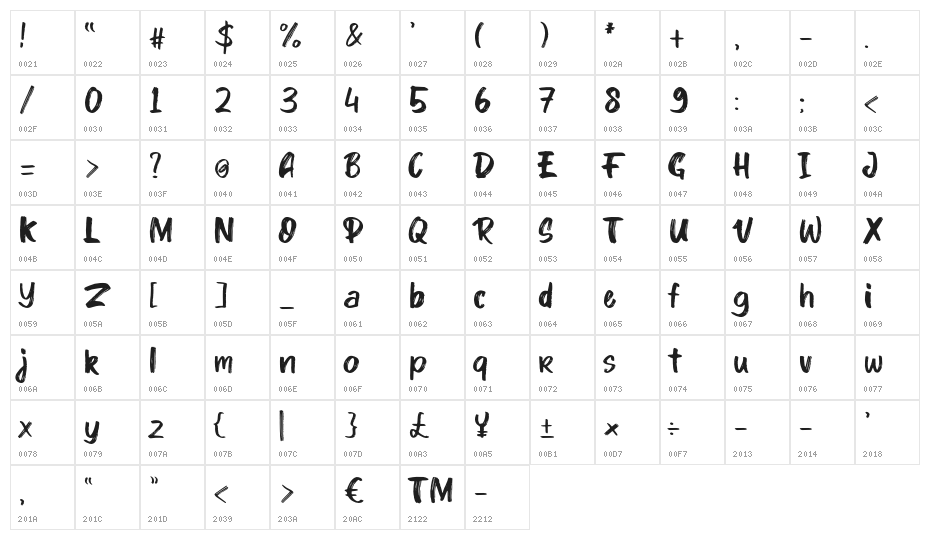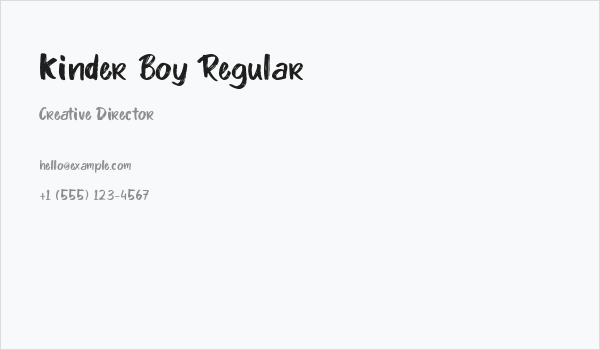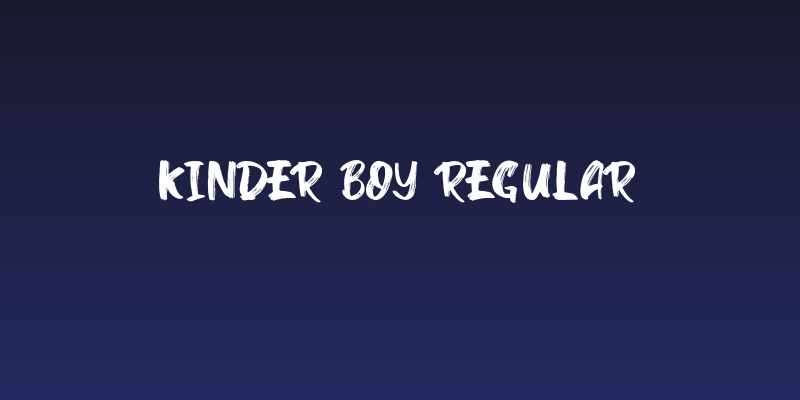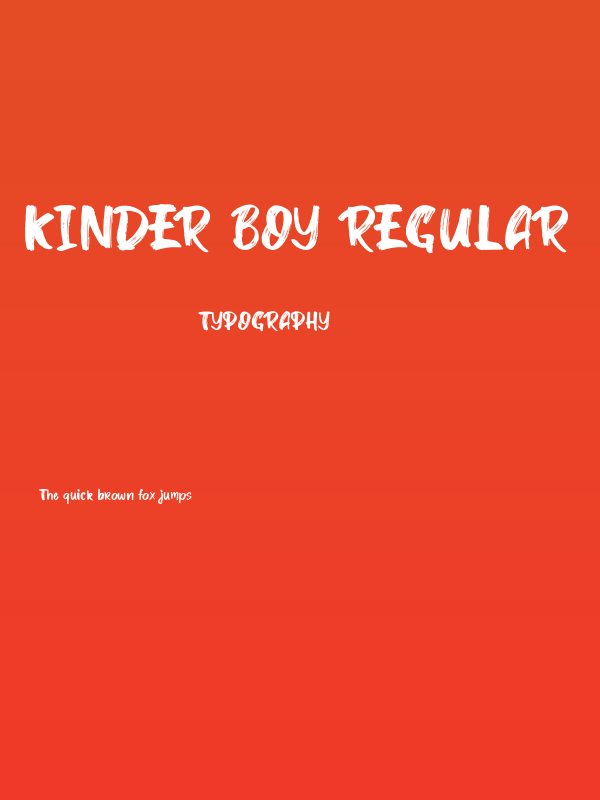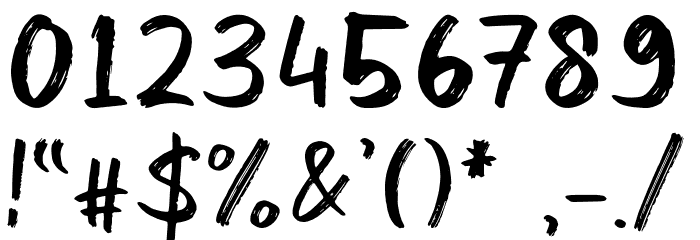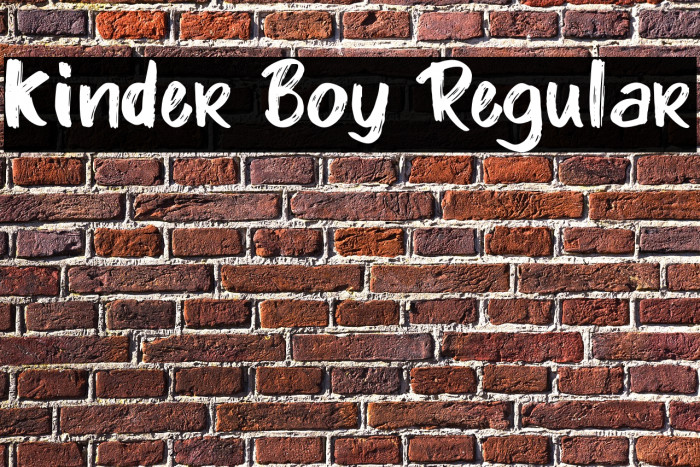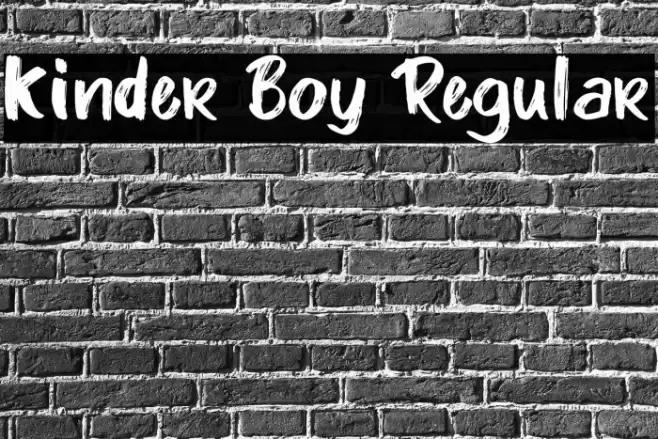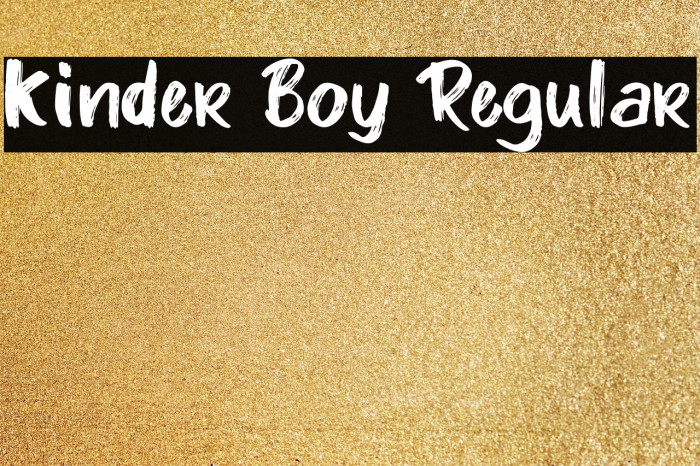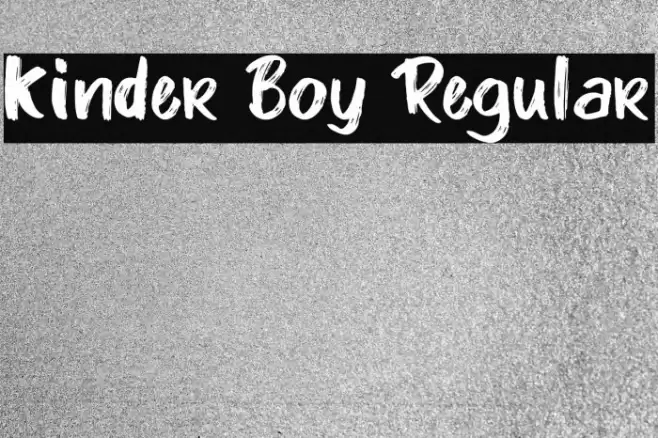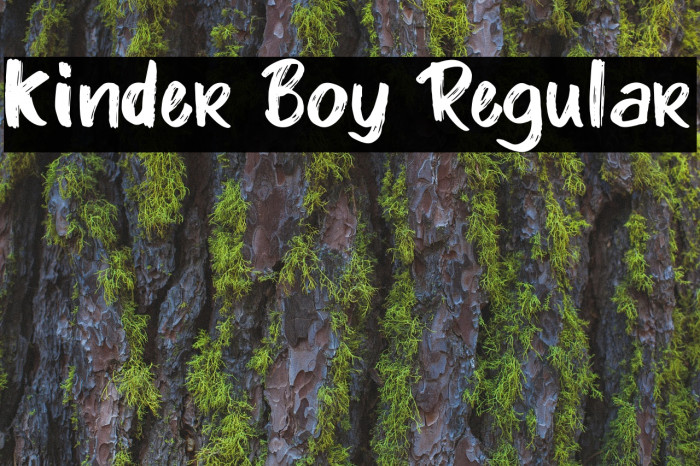
Kinder Boy Regular Font
| Estilo geral | Playful, Artistic |
| Projetos propostos | Ideal for children's book covers, playful branding, creative posters, and artistic social media graphics. |
| Autor | Fonts by william jhordy |